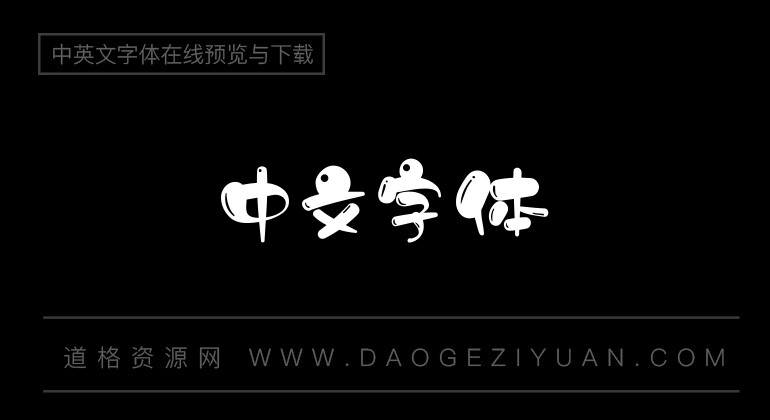
锐字温帅小可爱简
锐字温帅小可爱简是一款简洁可爱的字体,它的字母和符号都比较精细,且字形比较细腻,符号也比较简洁,易于阅读。它的字体比较细腻,字符比较紧凑,有着温暖的感觉,非常适合用于文字的排版,比如书写文章、排版文字等。
锐字温帅小可爱简是一款非常不错的手写艺术字体,具有很好的视觉感,适合于文化类的宣传设计、商业类品牌的广告和产品包装设计以及个性化文字排版等较多场景。
锐字温帅小可爱简字符映射图